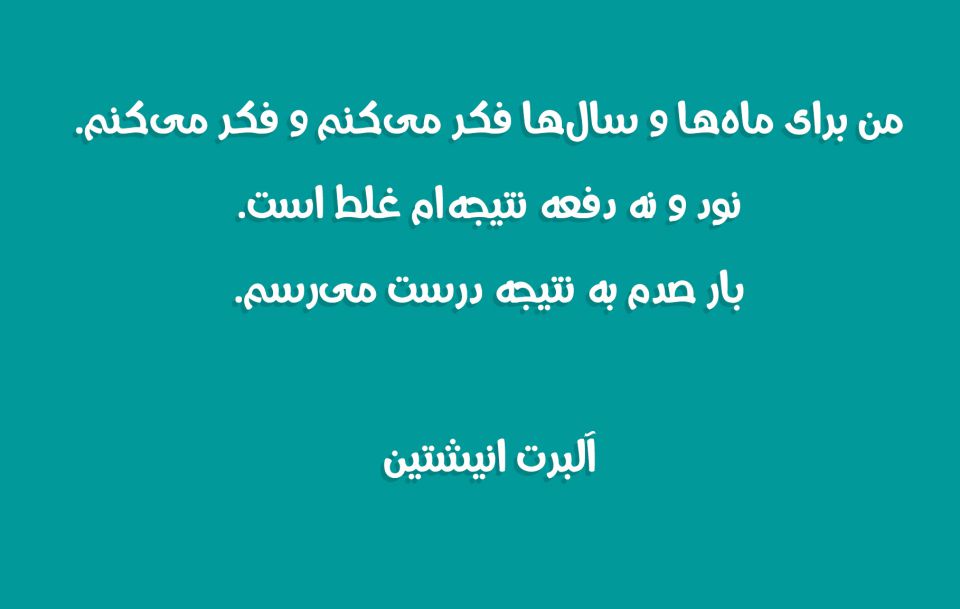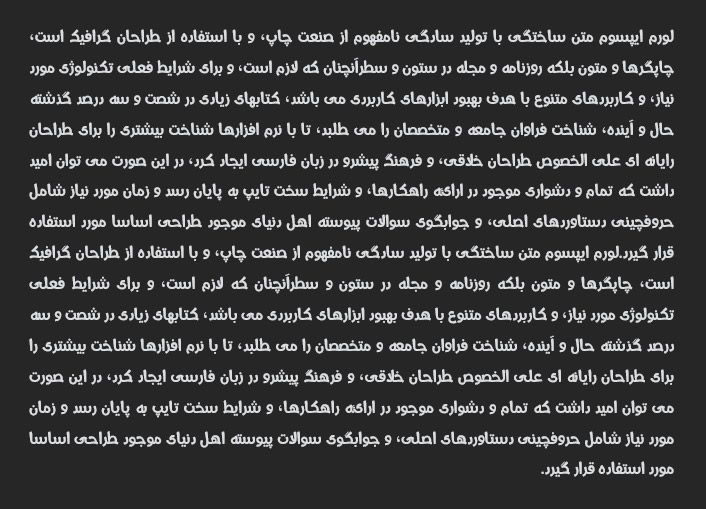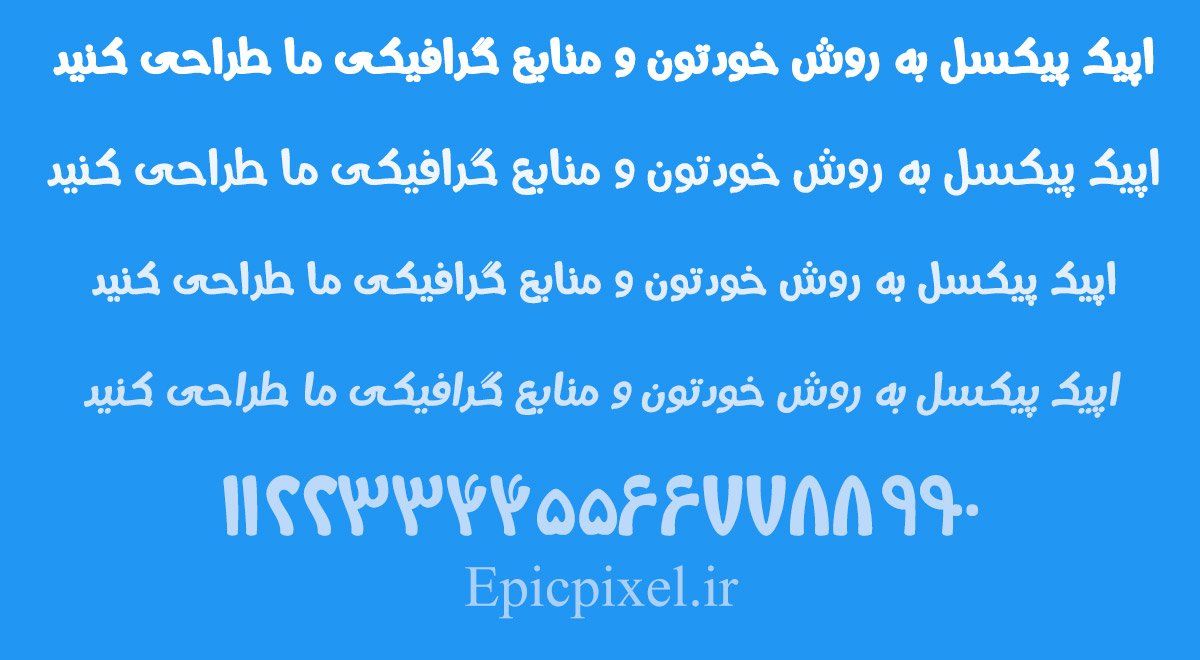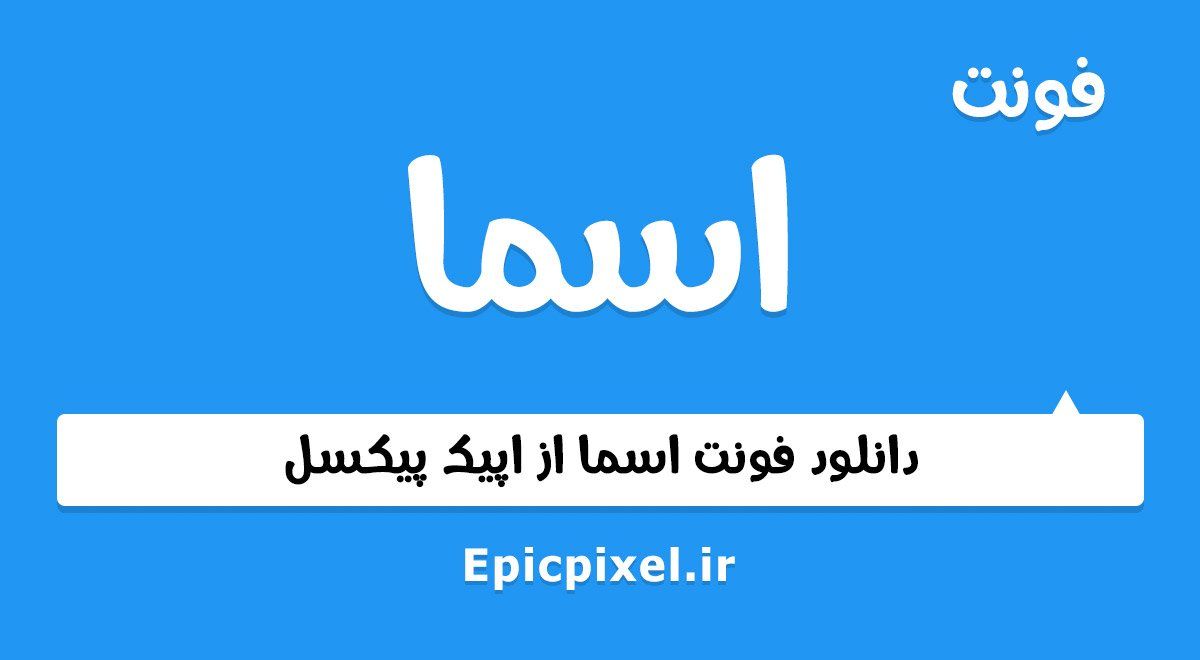
فونت اسما فارسی
| ⭐ توضیحات | دانلود رایگان فونت اسما زیباتر بنویسید، حرفهایتر طراحی کنید کاملا فارسی شده بهمراه نسخه انگلیسی با حروف کامل ی و ک و پژپچ
دانلود فونت اسما زیباتر بنویسید، حرفهایتر طراحی کنید
جستجو برای فونت اسما به دنبالهای از نتایج منجر میشود، اما آیا واقعاً بهترین گزینه برای پروژه شماست؟ در این مقاله جامع، به تمام جوانب دانلود فونت اسما، از ویژگیهای آن تا جایگزینهای احتمالی و نکات کلیدی برای انتخاب فونت مناسب، میپردازیم.
فونت اسما چیست؟
فونت اسما یک فونت تزئینی با ظاهری زیبا و منحنی است که برای طراحیهای خلاقانه و عناوین جذاب مناسب است. این فونت با الهام از خطوط عربی طراحی شده و حروف آن دارای جزئیات ظریف و کشیده هستند.
فونت اسما در دو نسخه فارسی و عربی ، انگلیسی در دسترس است. نسخه فارسی آن برای متون فارسی بهینه شده و خوانایی بیشتری دارد، در حالی که نسخه عربی برای نوشتن به زبان عربی مناسبتر است.
ویژگیهای کلیدی فونت اسما
- طراحی تزئینی: با حروف کشیده و جزئیات ظریف، فونت اسما ظاهری زیبا و متمایز به پروژههای شما میبخشد.
- خوانایی متوسط: خوانایی فونت اسما در اندازههای بزرگتر بهتر است. برای متنهای بدنه با حجم زیاد، ممکن است گزینه ایدهآلی نباشد.
- قابل استفاده برای عناوین و لوگوها: به دلیل زیبایی بصری، فونت اسما برای طراحی عناوین، لوگوها و المانهای برجسته ایدهآل است.
- پشتیبانی از الفبای فارسی و عربی: هر دو نسخه فارسی و عربی فونت اسما در دسترس است.
انتخاب فونت مناسب به عوامل مختلفی مانند ماهیت پروژه، مخاطب هدف و لحن کلی کار شما بستگی دارد. در اینجا چند نکته برای تصمیمگیری در مورد اینکه آیا فونت اسما برای پروژه شما مناسب است، وجود دارد:
- پروژههای خلاقانه: اگر به دنبال یک فونت تزئینی و جذاب برای پروژههای خلاقانه مانند پوستر، بروشور یا طراحی وبسایت هستید، فونت اسما میتواند انتخاب خوبی باشد.
- عناوین و لوگوها: برای طراحی عناوین، لوگوها و المانهای برجسته، فونت اسما به دلیل زیبایی بصری به خوبی عمل میکند.
- خوانایی در اولویت نیست: اگر خوانایی متن در اولویت نیست و میخواهید توجه مخاطب را به جلوههای بصری جلب کنید، فونت اسما گزینه مناسبی است.
با این حال، در نظر داشته باشید که:
- خوانایی متوسط: برای متنهای بدنه با حجم زیاد، به دلیل خوانایی متوسط فونت اسما، بهتر است از فونت دیگری استفاده کنید.
- پروژههای رسمی: اگر به دنبال یک فونت رسمی و ساده برای متون تجاری یا اداری هستید، فونت اسما انتخاب مناسبی نیست.
جایگزینهای فونت اسما
اگرچه فونت اسما یک فونت زیبا و خاص است، ممکن است برای همه پروژهها مناسب نباشد. در اینجا چند جایگزین برای فونت اسما آورده شده است:
- برای متنهای بدنه با خوانایی بالا: میتوانید از فونتهایی مانند فونت یکان ، فونت وزیر یا فونت کلمه استفاده کنید. این فونتها خوانایی عالی در اندازههای مختلف دارند و برای متنهای بدنه مناسب هستند.
- برای عناوین و لوگوهای رسمی: فونتهای سری فونت یکان و فونت شبنم گزینههای مناسبی برای عناوین و لوگوهای رسمی هستند. این فونتها خوانایی خوبی دارند و در عین حال حرفهای به نظر میرسند.
- برای فونتهای تزئینی با خوانایی بهتر: فونتهایی مانند فونت شیدا و فونت صمیم نیز گزینههای جالبی هستند. این فونتها تزئینی هستند اما خوانایی بهتری نسبت به فونت اسما دارند.
نکات مهم برای انتخاب فونت
هنگام انتخاب فونت برای پروژه خود، به نکات زیر توجه کنید:
دانلود- هدف پروژه: به ماهیت پروژه خود و پیامی که میخواهید منتقل کنید، فکر کنید.
- مخاطب هدف: فونتی را انتخاب کنید که با مخاطب هدف شما ارتباط برقرار کند.
- خوانایی: اطمینان حاصل کنید که فونت در اندازههای مختلف به راحتی قابل خواندن است.
- تطبیق پذیری: فونتی را انتخاب کنید که با سایر عناصر طراحی پروژه شما هماهنگ باشد.
2. آیا فونت اسما شامل تمام حروف الفبای فارسی و عربی است؟
بله، فونت اسما شامل تمام حروف الفبای فارسی و عربی است.